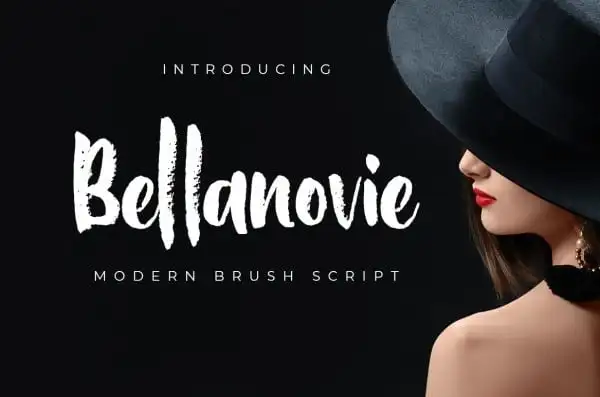
Descubra uma nova adição para sua biblioteca de fontes de script, a Bellanovie Brush Font. Esta criação é resultante dos toques suaves e desajeitados de um pincel manual, projetada por Nurf Designs no site da 99designs. Com seus traços ágeis e fluidos, essa fonte pode tornar suas mensagens em design mais expressivas, oferecendo uma impressão única de bold e aventura. Seu aspecto é um handwritten style, mas com um toque de textura de cera que o torna perfeitamente adaptável a uma variedade de aplicativos gráficos, desde criação promocional até logotipos, embalagens e identidades corporativas. Ideal para quem busca um desenho autêntico em sua próxima peça visual.